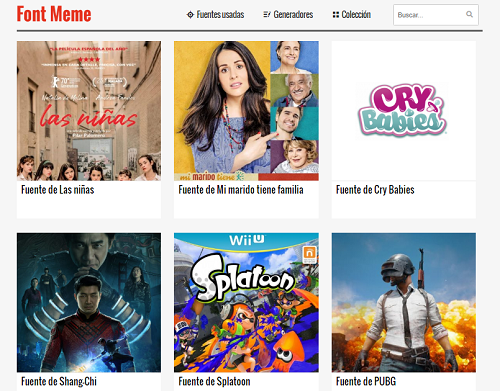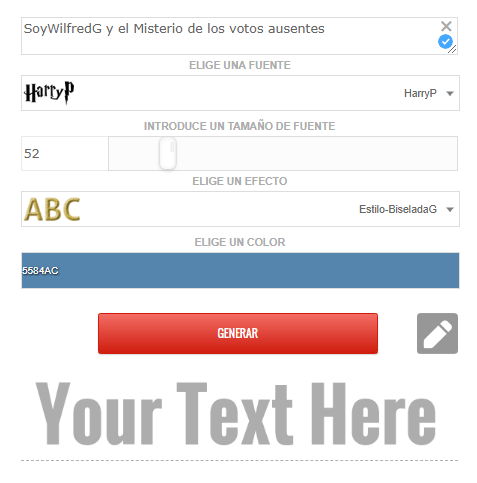
Descubre como utilizar textos con la tipografía de tu serie/película/marca favorita
¡Hola! Espero se encuentren muy bien, en esta ocasión, quiero aprovechar este miércoles de #CotinaTech para mostrarles una página dónde podrán encontrar y utilizar completamente gratis la tipografía de tu serie, película o marca favorita.
La página se llama fontmeme está en español y utilizarla es super fácil, a continuación, les muestro la interfaz:
Captura de la página principal de fontmeme
Usarla es muy sencillo, simplemente te desplazas por la página y buscas la fuente (tipografía) que más llame tu atención…
A fin de mostrarles cómo funciona, les daré dos ejemplos: Uno con la tipografía de Harry Potter y otra con la de Pokémon:
Captura de pantalla de la página
Lo primero es hacer clic sobre la imagen de la tipografía que queremos utilizar, lo primero que nos va a aparecer, será una breve descripción del origen de la fuente, tenemos que desplazarnos hacia abajo y nos mostrará lo siguiente:
Aplicando la tipografía
Luego de escribir el texto (primera línea) podremos escribir el estilo (algunas tipografías cuentan con diferentes estilos), en la tercera línea, podremos elegir el tamaño del texto, en la cuarta un efecto y en la quinta, el color… En lo que terminemos, hacemos clic en “Generar”
¡Y listo!
Este es el resultado:
Luego que hagan clic en “generar” les va a arrojar el texto en forma de imagen, simplemente deben hacer clic derecho sobre ella y guardarla/copiarla y pegarla en sus post como una imagen cualquiera.
Así queda la de Harry Potter (Esta tipografía tiene varias variantes que te invito a que las descubras)
Y la de Pokémon se ve así:
Las de Harry Potter y Pokemón, están en la página 8
En total, hay más de 200 fuentes diferentes que pueden usar las veces que quieran!! Todas se usan de la misma forma
¿Fácil, no?
Este tipo de fuentes son excelentes para utilizarlas como separadores, como encabezados, cómo títulos o como mejor nos parezca!!
Si si se puede!! Las letras te van a salir en formato imagen (png) y ahí podrás ponerla del tamaño que quieras y en la posición que elijas 😁😁
Lo mejor es que la calidad de la imagen es alta así que seguro que se verán genial en tus creaciones 😁😁